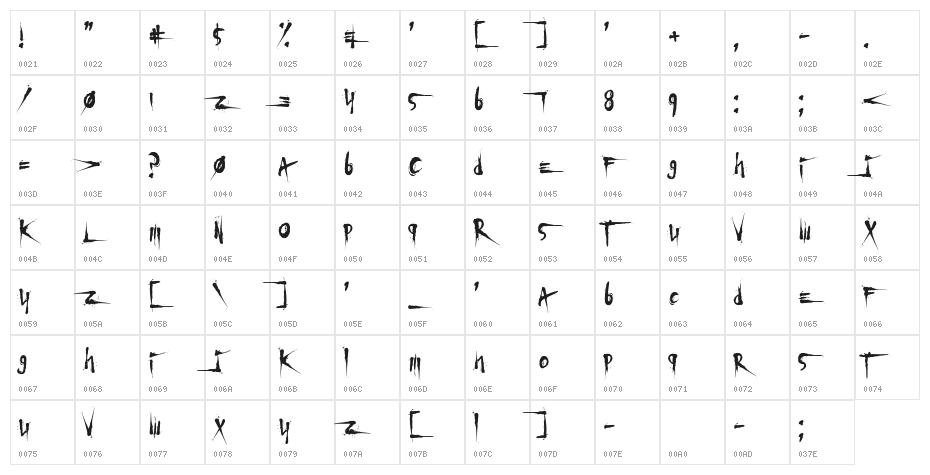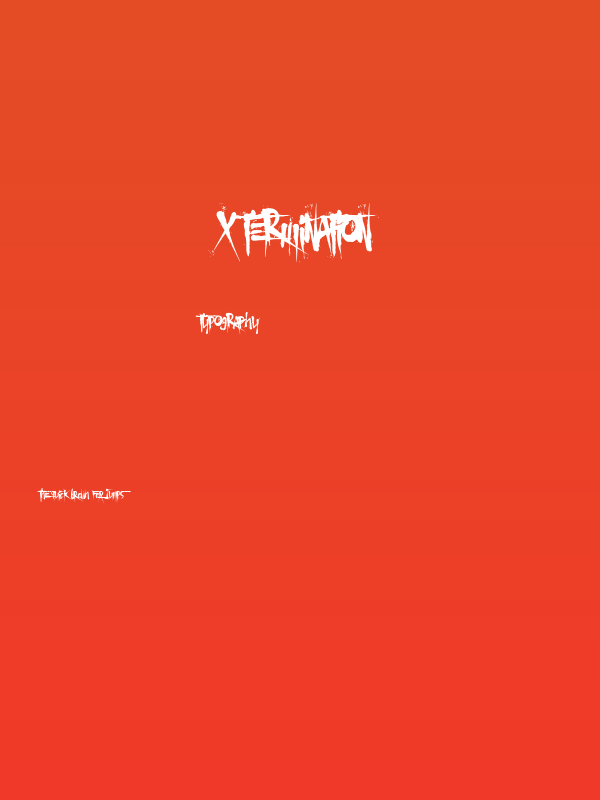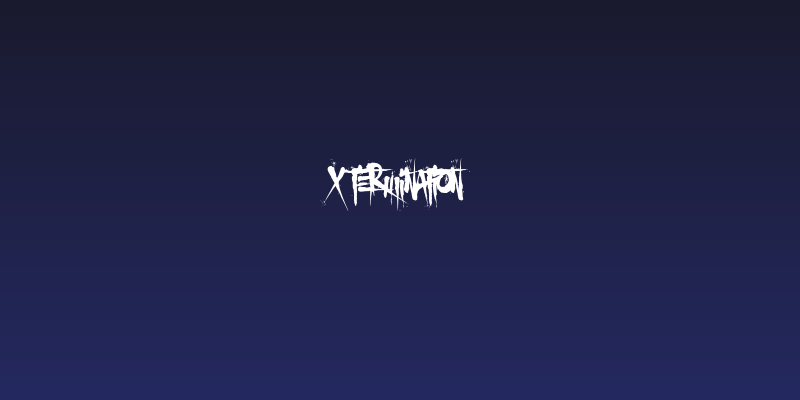
X Termination Font
✎ Graffiti
| Categorie | Graffiti |
| Stile generale | Urban, Rebellious, Energetic |
| Progetti proposti | Ideal for street art designs, music album covers, event posters, and edgy branding. |